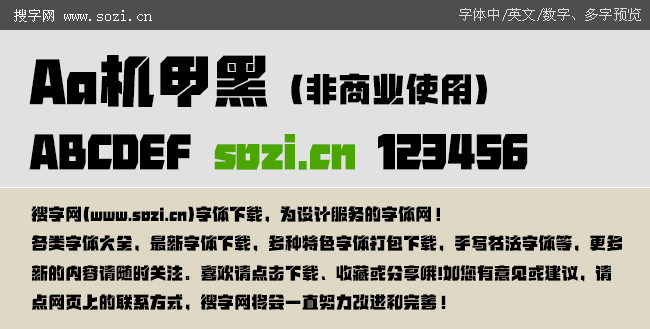
Aa機(jī)甲黑
搜字網(wǎng)給大家提供一款A(yù)a機(jī)甲黑(非商業(yè)使用)中文字體下載,Aa機(jī)甲黑是一款獨(dú)具特色的字體,以簡(jiǎn)單斜切的筆畫和方正飽滿的結(jié)構(gòu)體現(xiàn)機(jī)械冷靜卻充滿力量的科技感,通過斜切的白空間表現(xiàn)機(jī)械結(jié)構(gòu)間的疊壓拼合,迎合用戶對(duì)于極粗字體的使用需求。 適合應(yīng)用于海報(bào)設(shè)計(jì)、包裝設(shè)計(jì)、網(wǎng)頁(yè)設(shè)計(jì)等應(yīng)用(此字體為個(gè)人非商用版,商用可以聯(lián)系QQ:1006760504)。